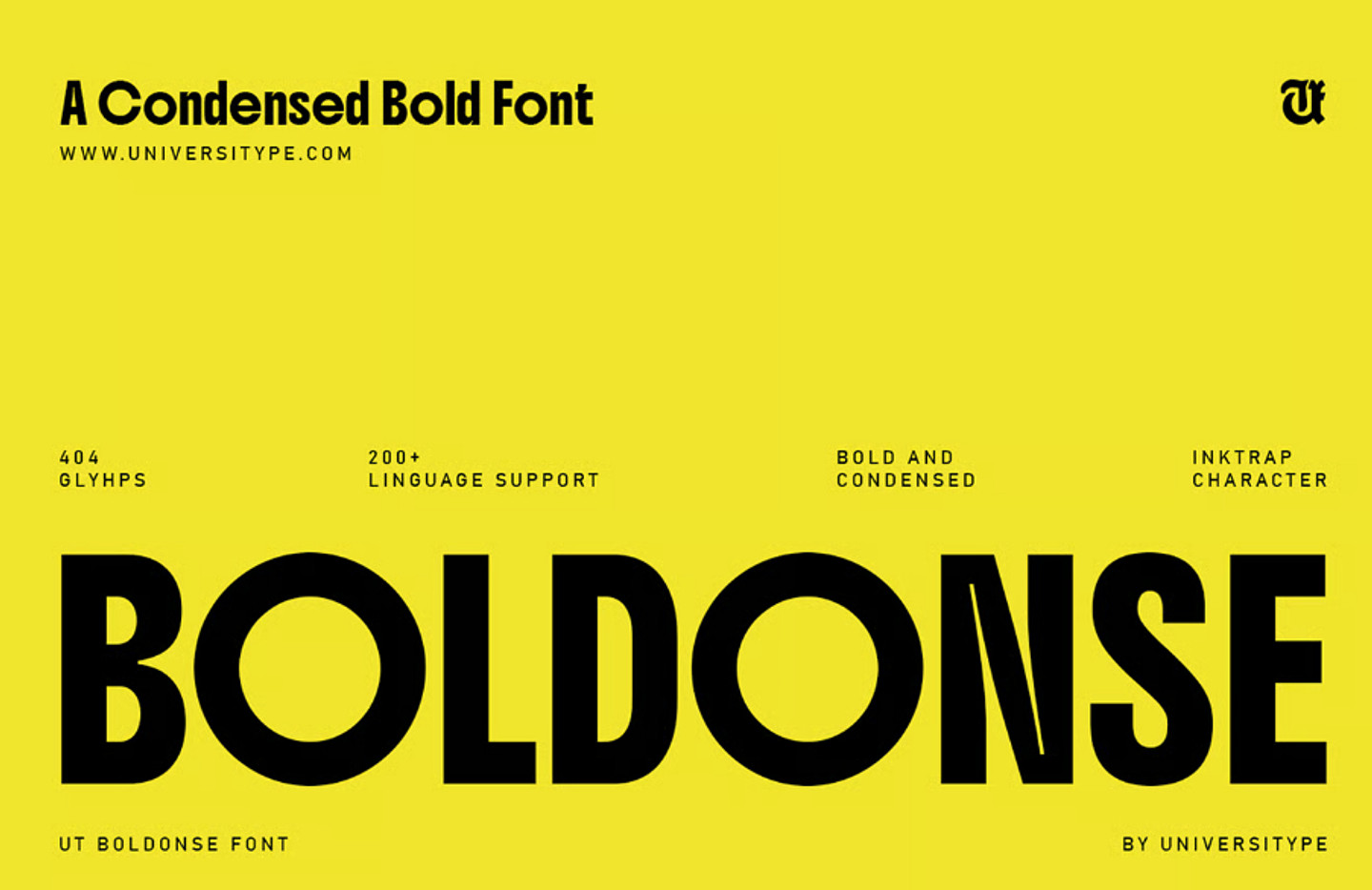
O랑 G가 큰 폰트인데 도저히 못찾겠습니다 ㅠㅠ 영어에 쓰인 폰트가 뭔지 찾고 있습니다. 제발 도와주세요 ㅠㅠ https://www.artic.or.kr/base/board/read?boardManagementNo=1&boardNo=3871&searchCategory=&page=1&searchType=total&searchWord=%EB%9D%BC%EC%9D%B8%EC%97%85&menuLevel=3&menuNo=48 해당 링크에 볼드체로 쓰인 영어랑 숫자 폰트입니다 ㅠㅠ
Boldonse
N의 형태로 보아 이 폰트가 맞는 것 같습니다~